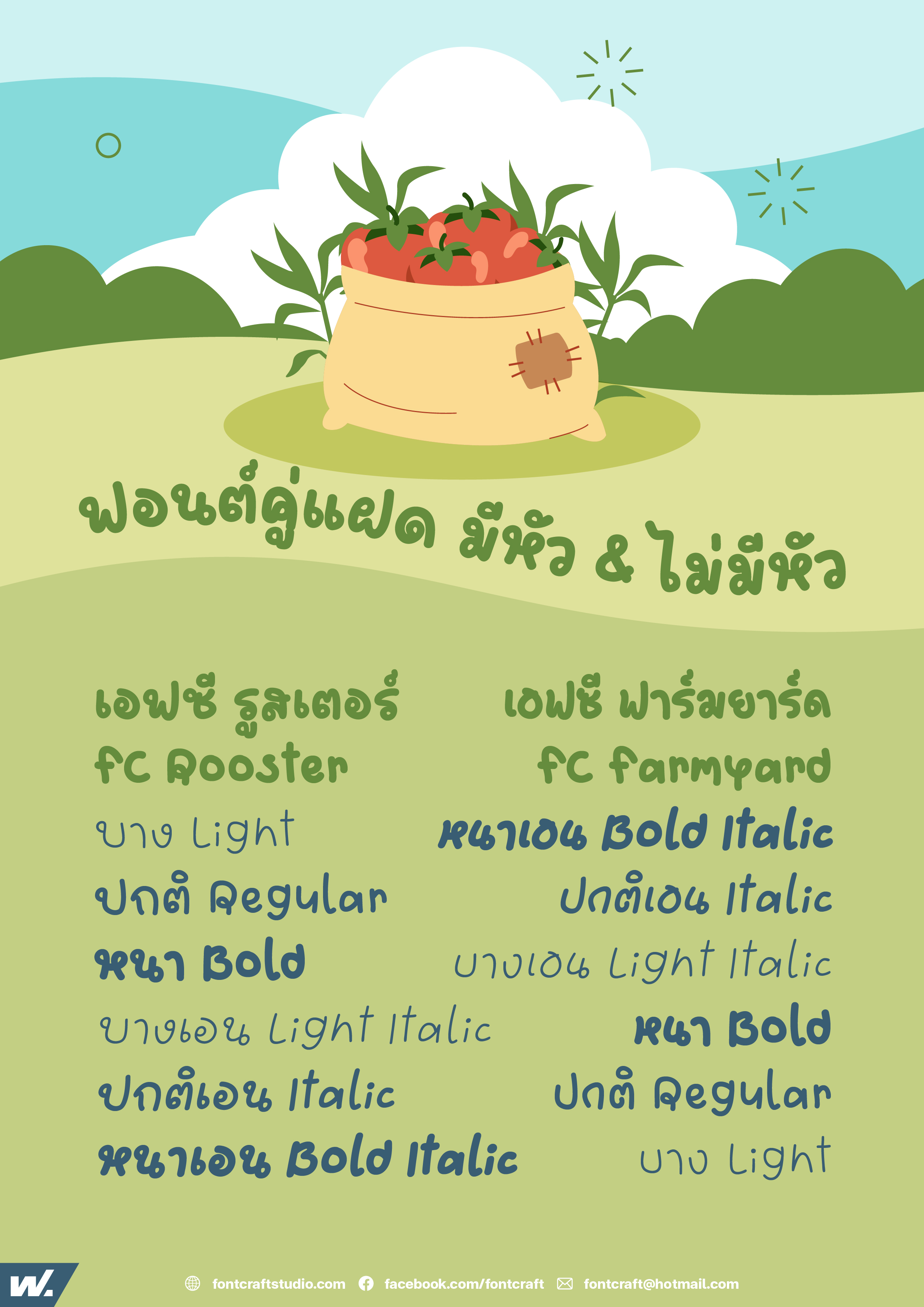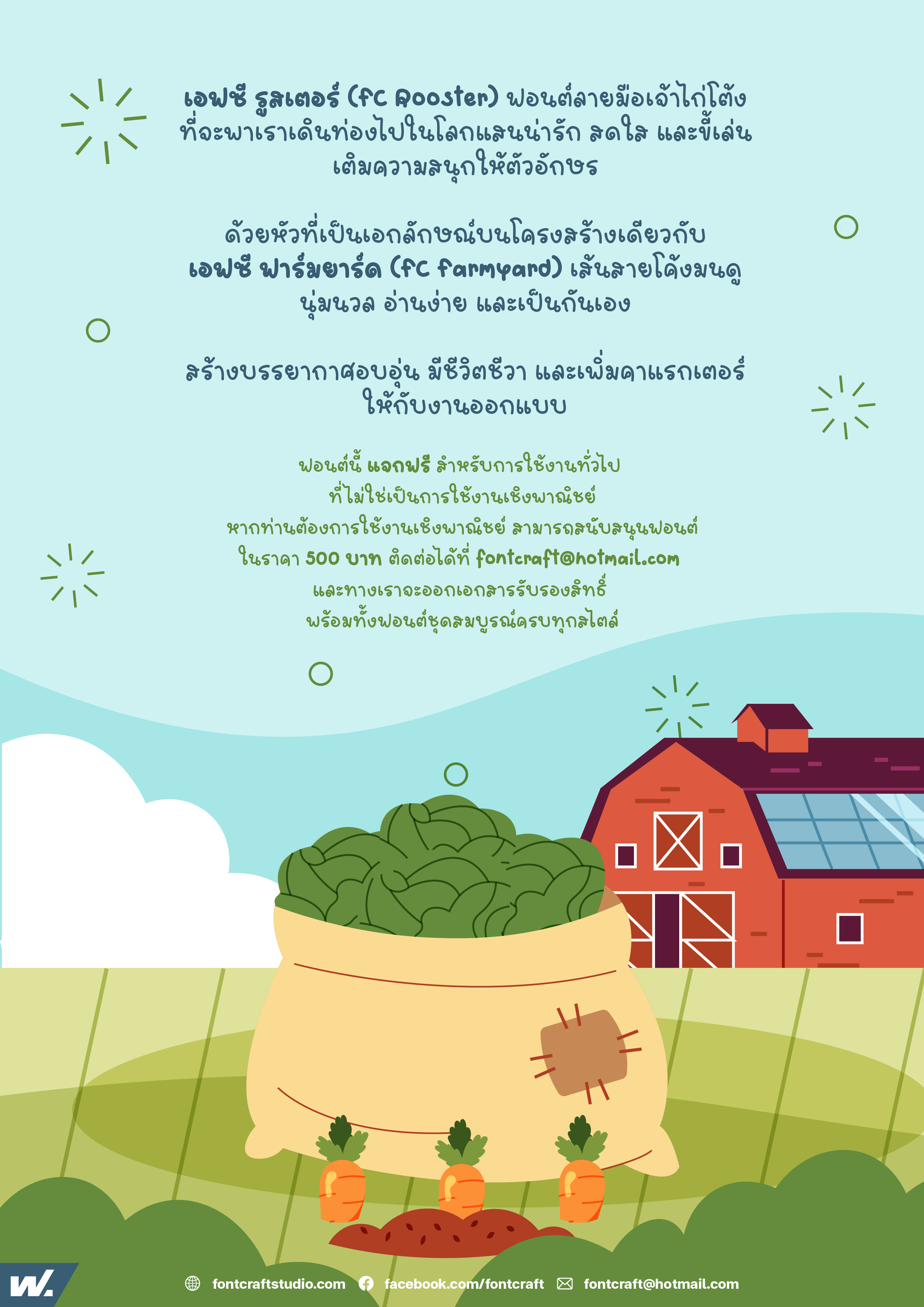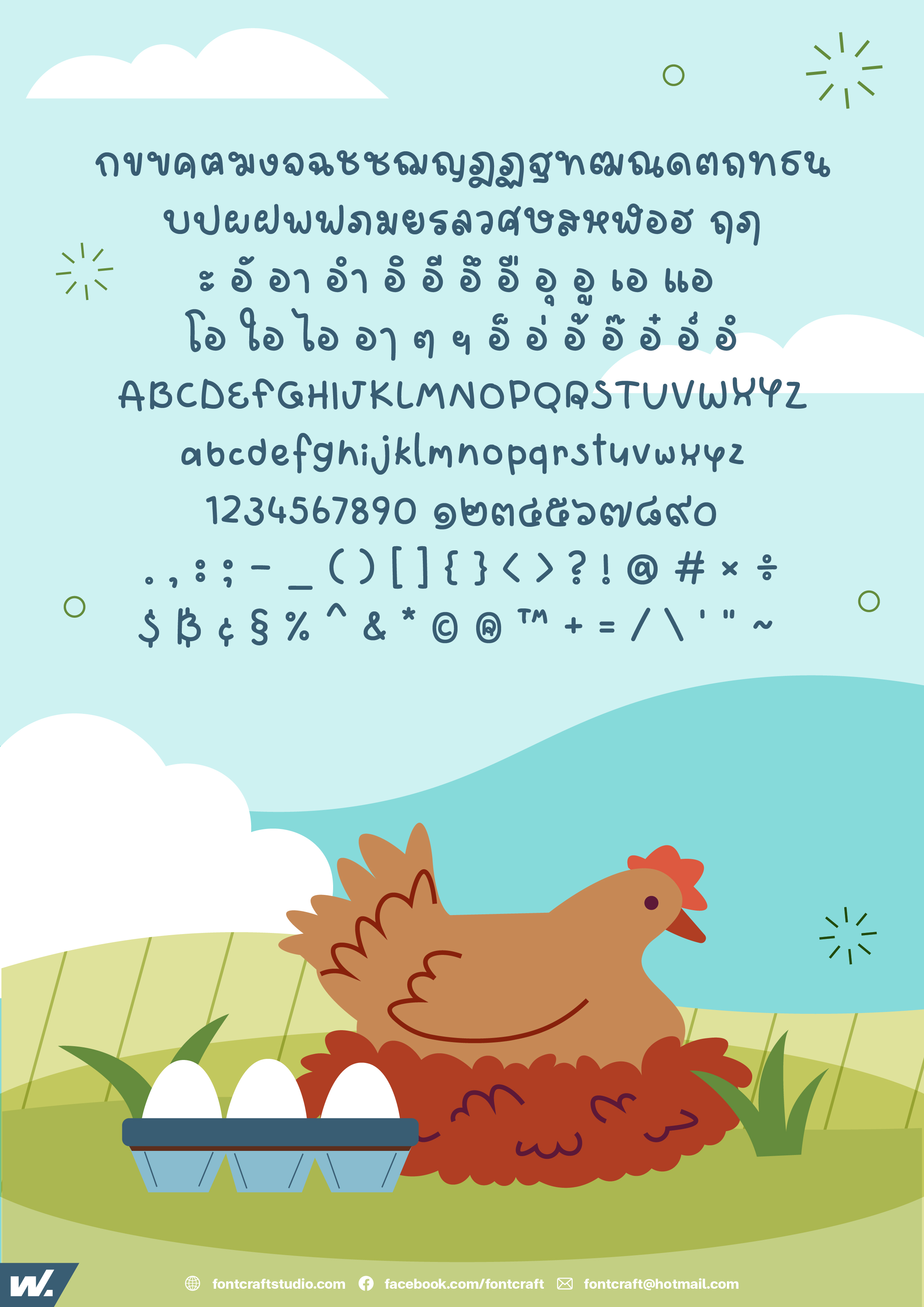
เอฟซี รูสเตอร์ (FC Rooster)
ฟอนต์เอฟซี รูสเตอร์ (FC Rooster)
ฟอนต์ลายมือเจ้าไก่โต้งที่จะพาเราเดินท่องไปในโลกแสนน่ารัก สดใส และขี้เล่น เติมความสนุกให้ตัวอักษรด้วยหัวที่เป็นเอกลักษณ์บนโครงสร้างเดียวกับฟอนต์เอฟซี ฟาร์มยาร์ด (FC Farmyard) เส้นสายโค้งมนดูนุ่มนวล อ่านง่าย และเป็นกันเอง ช่วยสร้างบรรยากาศอบอุ่น มีชีวิตชีวา และเพิ่มคาแรกเตอร์ให้กับงานออกแบบ
มาพร้อม 3 ระดับน้ำหนัก บาง ปกติ หนา และตัวเอน รวม 6 สไตล์